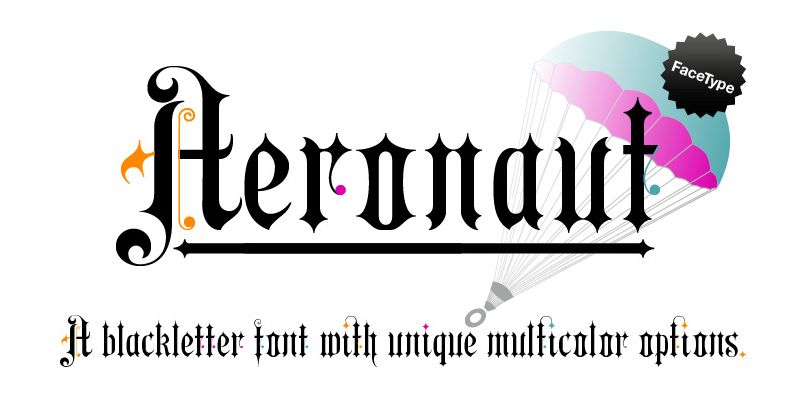
Hỏi tên font gì? Hỏi xin font chữ thì post vào đây! Ko lập topic mới
Font đó tên gì thế? :))
Ai cho mình hỏi STRENGTH là font gì với ?
Các bạn cho mình hỏi font chữ như trong hình tên gì và nếu có cho mình link down (:
À mà cho mình hỏi tên các font hay dùng trong các tạp chí (phần nội dung bài viết ý) (:
Alittlecloser: san serif kiểu đó là có mà đầy ra, Tahoma, Arial, Helvetica,... Làm sao nói chính xác tên được bạn.
newvietdesigner: tạp chí thì đầy các font serif kiểu Times New Roman bạn ơi.
N.P Ừm! Nếu vậy bạn cố gắng giúp mình hai yêu cầu còn lại nhé
Cho em hỏi font "myx" ở phía bên phải là gì ạ. Tìm hoài không thấy :((
Cho mình hỏi font này là font gì được không? nếu không thì cho mình vài cái font kiểu như vậy nha!
cho mình hỏi font cao bồi không gian là font ji vậy
Cho mình hỏi là mình có bản Việt hóa của font PF Square Sans Pro Regular không vậy :)